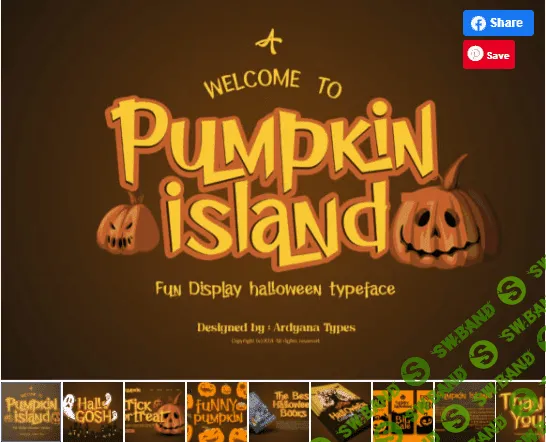
Название: Pumpkin Island Font (2021)
Pumpkin Island - непринужденный и пугающий дисплейный шрифт. Он олицетворяет игривость и аутентичность и является идеальным выбором для любого детского мероприятия или школьного проекта.